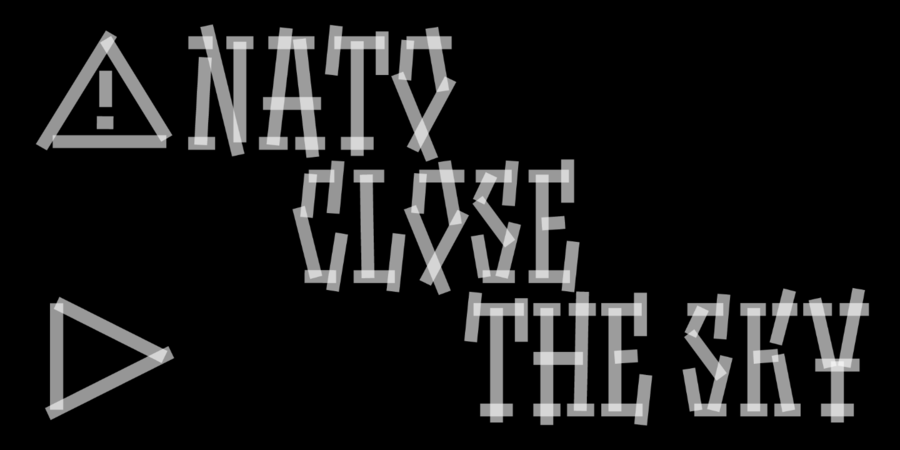
Opir (1 шрифт)
Минуло майже два тижні після підлого нападу росії на Україну, а українські захисники весь час стримують натиск і чинять колосальний опір. Саме цьому опору я присвячую цей шрифт. Це надихає та мотивує мене.
Графіка шрифту базується на смугах скотчу, наклеєного на шибки. Це символізує опір та обережність. Такі реалії нашого сьогоднішнього життя в Україні.
Це версія 1.0 підтримує лише англійську та українську. Також багато символів, які можна знайти в таблиці гліфів у різних графічних програмах. Це кольоровий напівпрозорий шрифт. Колір та прозорість можна редагувати, переводячи літери в криві. Шрифт розробив Максим Кобузан у 2022 році.